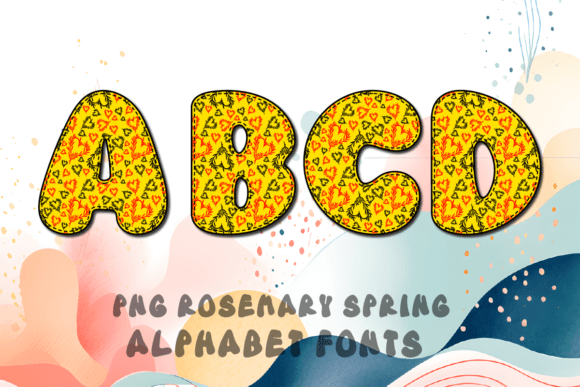
Rosemary Spring Alphabet Fonts
إذا كنت تبحث عن أصول عالية الجودة مثل Rosemary Spring Alphabet Fonts، فإن هذه الحزمة المميزة هي خيار رائع لمشاريعك الإبداعية.
سواء كنت تقوم بإنشاء منتجات الطباعة عند الطلب أو دعوات الزفاف أو رسومات وسائل التواصل الاجتماعي، فإن Rosemary Spring Alphabet Fonts هو الخيار المثالي.